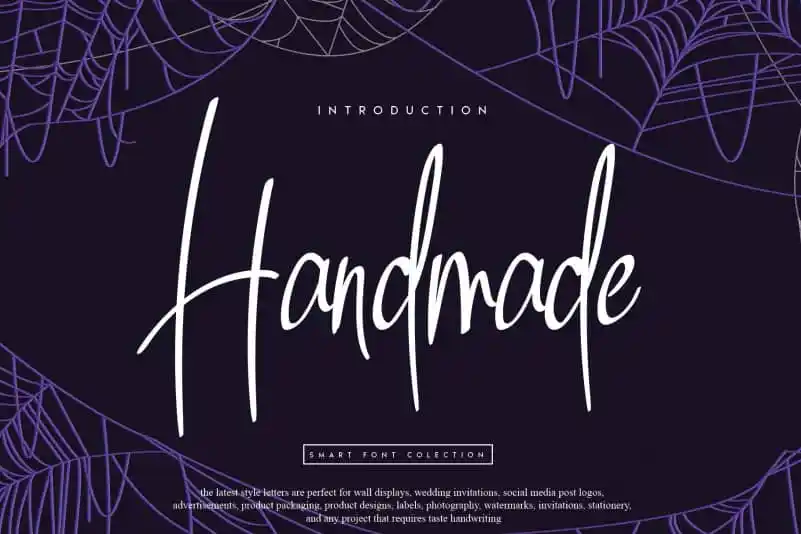
Handmade Script Font – Download Grátis
A Handmade Script Font é uma excelente adição para designers que buscam um recurso de escrita personalizada e criativa. Essa fonte foi desenvolvida por andikastudio, oferecendo textos elaborados e sutis, capazes de dar vida a qualquer projeto visual. A sua natureza única permite dar um toque especial aos seus designs, destacando-os na multidão com seu charme único e detalhado estilo gráfico. A fonte é perfeitamente adaptada para projetos que exigem um equilíbrio entre elegância e originalidade. Seja em publicações online ou materiais impressos, ela proporcionará uma experiência visual única, destacando-se em qualquer ambiente de design. Como parte da categoria de Fonts Handwritten, a Handmade Script Font é uma escolha ótima para quem procura um recurso que combine conforto visual com personalidade. A fonte oferece uma variedade de recursos para garantir uma experiência de uso fluida e gratificante, combinando facilidade de digitação com resultados visuais impactantes. Seja você designer gráfico, publicitário ou criativo em geral, a Handmade Script Font certamente se encaixa perfeitamente na sua paleta de ferramentas para trazer uma nova dimensão à sua arte.